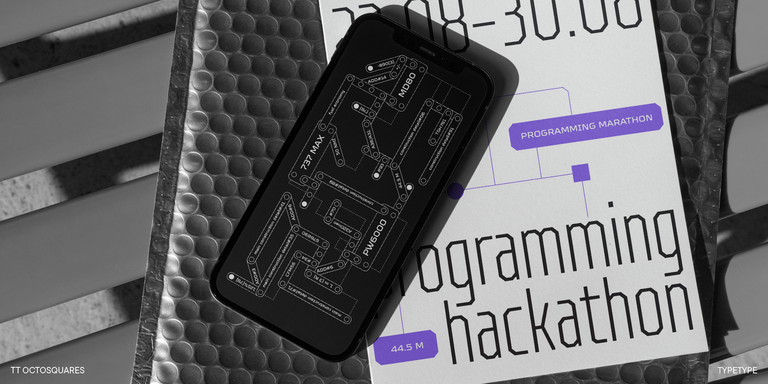
TT Ricordi Allegria ist eine elegante und intelligente zeitgenössische florentinische Grotesk.
Sonnenaufgang-Schriften
TT Firs Neue ist eine zeitgemäße Reinkarnation der guten alten serifenlosen TT Firs.
TT Octosquares ist eine frische, überarbeitete, erweiterte und deutlich verbesserte Version unserer ersten kommerziellen Schrift TT Squares und ihrer schmalen Variante.
TT Polls ist eine moderne modulare Slab-Serif-Familie für den Einsatz im Sportdesign.
Ohne falsche Bescheidenheit können wir sagen, dass TT Lovelies Script eines der komplexesten Projekte ist, die wir je umgesetzt haben: 1115 Glyphen, mehr als 2000 kontextuelle Alternativen, 10.000 Kerning-Paare und eine große Anzahl an OpenType-Features, darunter Ligaturen und Mediävalziffern.